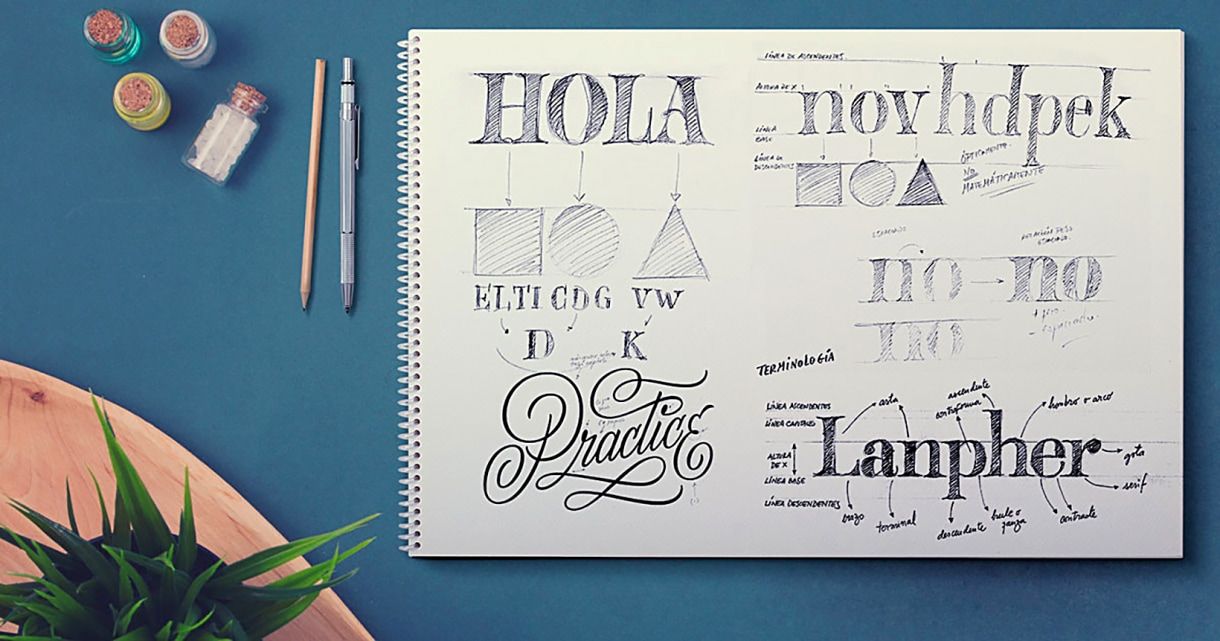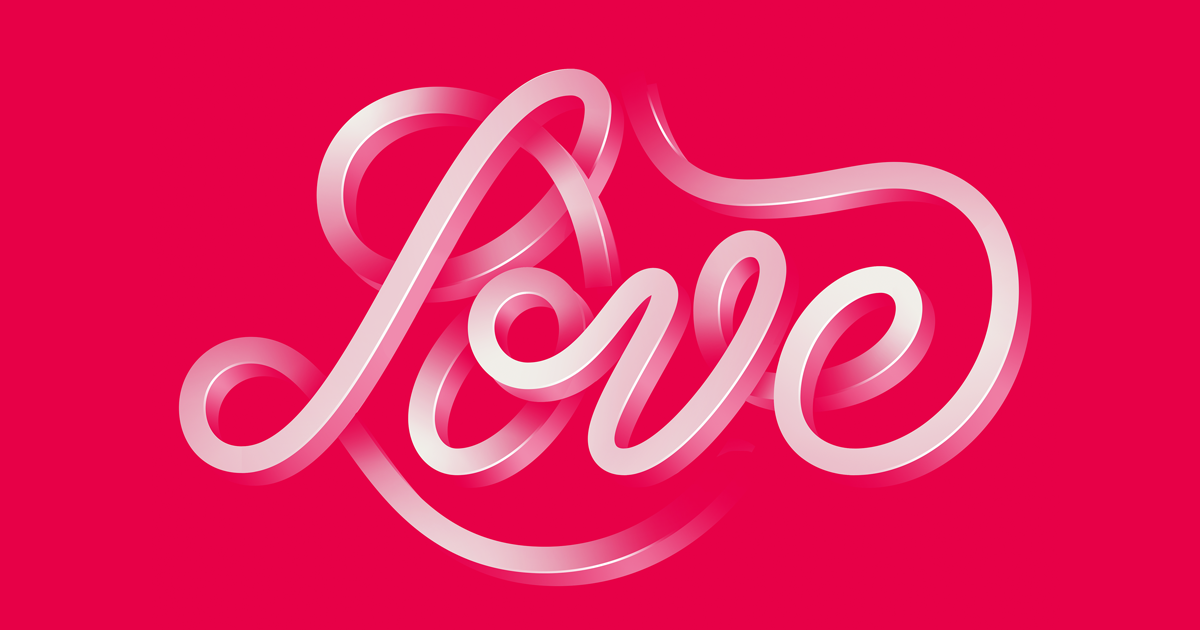
Lettering, calligrafia e tipografia: conosci le differenze?
Tutte e tre sono discipline che coinvolgono le lettere…e questa è forse l'unica cosa che hanno davvero in comune
La creazione di lettere e caratteri è un mondo vario e complesso, non c’è perciò da sorprendersi se tra i non addetti ai lavori ci sono alcuni dubbi a riguardo. In questo articolo cerchiamo di spiegare cosa sono esattamente il lettering, la calligrafia e la tipografia, e quali differenze le distinguono tra loro. Descriveremo le caratteristiche di ogni disciplina e mostreremo esempi per aiutarti a riconoscerle. Speriamo che, dopo aver letto questo post, sarai in grado di evitare la confusione tipica (e giustificata!) di designer alle prime armi, o creativi specializzati in altre aree.
Calligrafia
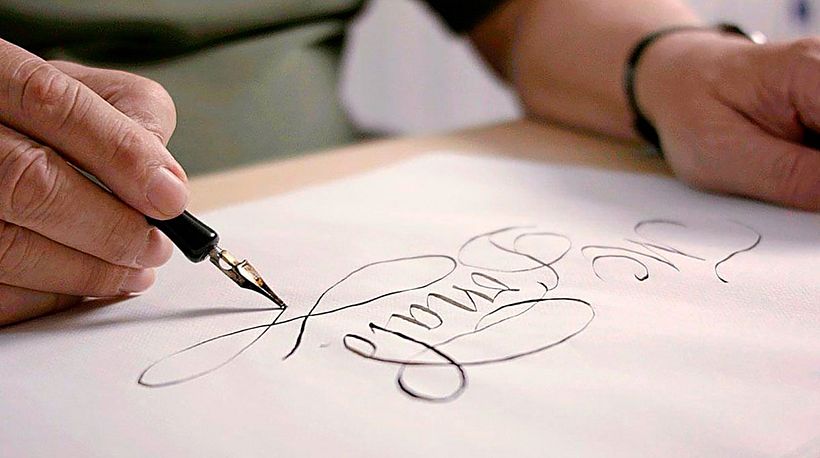
Questa disciplina consiste nello scrivere lettere prestando particolare attenzione a come viene creato ogni tratto e agli elementi che formano ogni segno dell’alfabeto, esaminando velocità, direzione e sequenza. La calligrafia è sempre fatta a mano, di solito con penne, pennarelli o pennelli. Si possono usare anche mezzi digitali, come ad esempio un tablet, purché la lettera sia disegnata a mano. Ogni parte chiave del carattere deve essere creata usando un solo tratto e non è permesso fare correzioni, questo significa che ogni lettera è unica. L'autore di una calligrafia è la persona che l'ha disegnata.
Lettering
A differenza della calligrafia, il lettering consiste nel disegnare lettere o parole, non nello scriverle, e l'autore è autorizzato a fare correzioni. Un'altra cosa che rende il lettering diverso dalla calligrafia è che le lettere possono essere create a mano o usando vettori o altri metodi digitali. Questo significa che non tutte le lettere saranno necessariamente uguali, ma possono essere copiate per dare all'insieme un aspetto più uniforme. L'autore di un progetto di lettering sarà la persona che ha disegnato le lettere, il che non è il caso quando si tratta di tipografia.
Tipografia
I designer di caratteri tipografici non creano lettere o segni unici come i calligrafi, né disegnano parole come gli artisti del lettering. Un carattere tipografico è un insieme unico di caratteri uniti da scelte stilistiche. Un type designer non solo disegna le lettere, ma le programma e stabilisce una serie di parametri chiave che si ripetono sistematicamente in tutto l'insieme di caratteri.